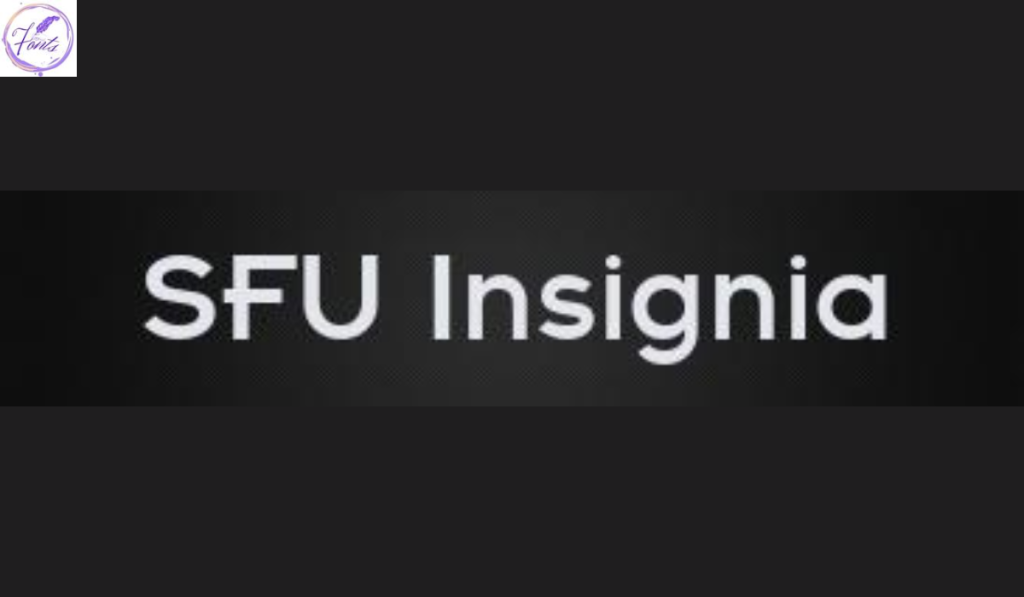
SFU Insignia Font Việt hóa
Tác giả: Simon Fraser University
Ngày phát hành: 2016
Ngôn ngữ: Tiếng Việt, Tiếng Anh, và nhiều ngôn ngữ khác
Bộ Font: SFU Insignia
Phân loại: Hiện đại, Thanh lịch, Chuyên nghiệp
Kiểu chữ: Sans-serif
Độ dày: Light, Regular, Bold, Black
SFU Insignia Font là một font chữ thuộc bộ font SFU mang phong cách vô cùng ấn tượng, được phát triển bởi Simon Fraser University vào năm 2016. Font chữ này mang phong cách hiện đại với các đường nét gọn gàng, sắc sảo, thích hợp cho các dự án thiết kế đòi hỏi sự nổi bật và sang trọng. SFU Insignia Font hỗ trợ đa ngôn ngữ và bao gồm đầy đủ các ký tự, giúp bạn dễ dàng sử dụng trong nhiều loại dự án khác nhau như thiết kế đồ họa, in ấn, và truyền thông.
Đánh giá sfu insignia font
SFU Insignia Font đã nhận được nhiều đánh giá tích cực từ cộng đồng thiết kế nhờ vào sự độc đáo và dễ sử dụng của nó. Font chữ này được khen ngợi vì khả năng mang lại cảm giác chuyên nghiệp và thanh lịch cho các dự án thiết kế. Đặc biệt, phiên bản Việt hóa của SFU Insignia Font giúp người dùng tại Việt Nam có thể tận dụng tối đa các tính năng mà không gặp bất kỳ trở ngại nào. Đây là một font chữ lý tưởng cho những ai muốn tạo nên sự khác biệt và nổi bật.